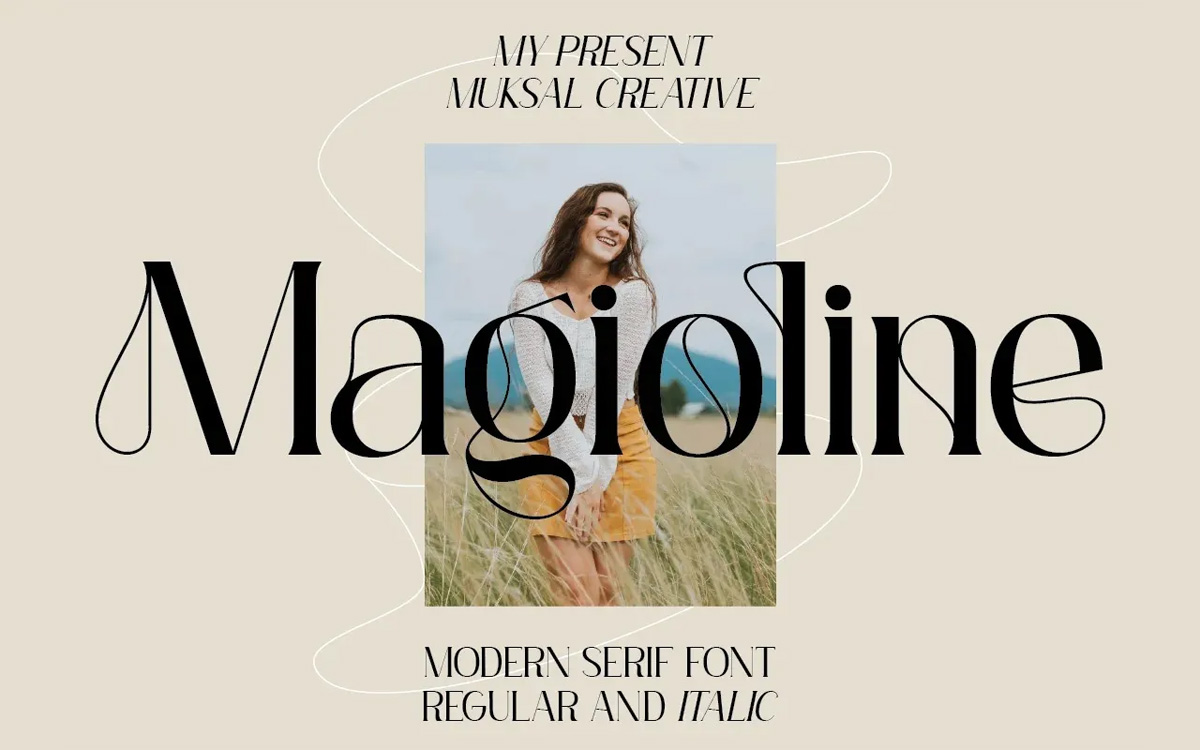
Chia Sẻ Font Chữ Việt Hóa TH Magioline – Vẻ Đẹp Của Sự Thanh Lịch Và Sang Trọng
Nếu bạn đang tìm kiếm một phông chữ mang đậm nét cổ điển nhưng vẫn toát lên vẻ hiện đại và tinh tế, thì TH Magioline chắc chắn là một sự lựa chọn không thể bỏ qua. Đây là một typeface được thiết kế với những đường nét mềm mại, tỉ mỉ, rất phù hợp cho các dự án thiết kế đòi hỏi tính thẩm mỹ cao.
🌟 Điểm Nổi Bật Của Font TH Magioline Việt Hóa
Font chữ TH Magioline đã được Việt hóa hoàn chỉnh, chăm chút kỹ lưỡng từng dấu câu để đảm bảo trải nghiệm gõ tiếng Việt mượt mà nhất trên các phần mềm thiết kế.
• Đường nét tinh tế: Sự kết hợp hoàn hảo giữa nét thanh và nét đậm tạo ra một tổng thể hài hòa, bắt mắt và vô cùng cuốn hút.
• Hỗ trợ tiếng Việt chuẩn xác: Kerning (khoảng cách giữa các chữ) và các dấu câu tiếng Việt được tùy chỉnh lại để không bị lỗi hiển thị hay dính chữ.
• Ký tự thay thế đa dạng (Alternate/Ligature): Giúp bạn thỏa sức sáng tạo và biến tấu các con chữ theo phong cách riêng của mình.
🎨 Ứng Dụng Của Font TH Magioline
Với sự thanh lịch vốn có, TH Magioline cực kỳ đa dụng và tỏa sáng nhất khi được áp dụng vào các ấn phẩm mang tính nghệ thuật hoặc thương mại cao cấp:
• Nhận diện thương hiệu: Thiết kế Logo, Slogan cho các thương hiệu thời trang, mỹ phẩm, spa, nhà hàng cao cấp.
• Ấn phẩm sự kiện: Làm typography cho thiệp cưới, thiệp mời, giấy chứng nhận.
• Thiết kế in ấn & Digital: Chèn chữ nghệ thuật lên hình ảnh, thiết kế bao bì sản phẩm, poster phim, banner quảng cáo mạng xã hội, hoặc làm tiêu đề (Heading) cho tạp chí, blog.